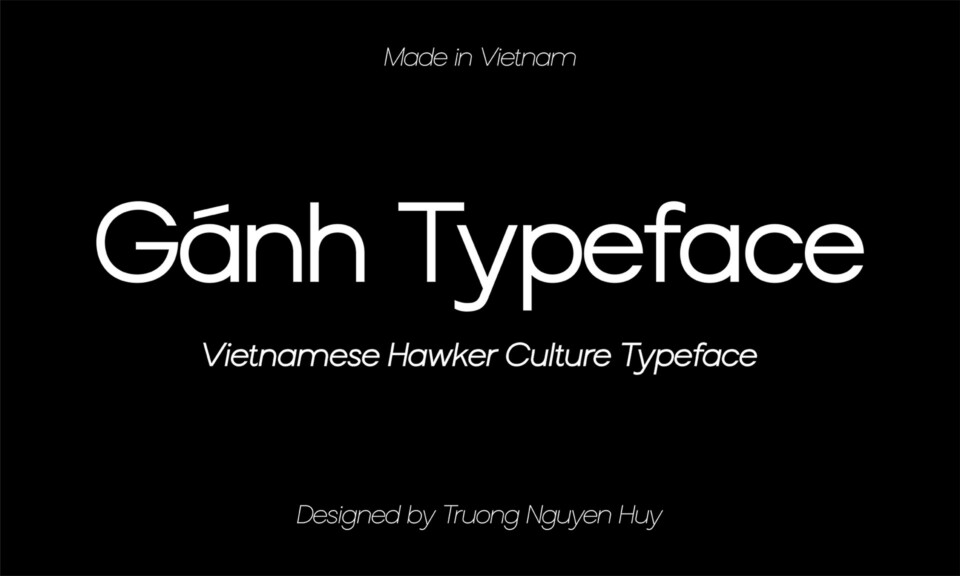
Font Gánh Typeface (4 otf files)
Giới thiệu về Font Gánh Typeface (4 otf files) và ý nghĩa thiết kế
Trong thế giới đồ họa hiện đại, việc tìm kiếm một bộ Font Miễn Phí mang đậm bản sắc văn hóa Việt Nam là điều vô cùng quý giá. Font Gánh Typeface (4 otf files) là một tác phẩm nghệ thuật chữ viết độc đáo, lấy cảm hứng từ hình ảnh đôi quang gánh tần tảo của người phụ nữ Việt. Bộ font này không chỉ đơn thuần là những ký tự số hóa mà còn chứa đựng cả một câu chuyện về sự nhẫn nại và nét đẹp lao động truyền thống. Với cấu trúc linh hoạt và đường nét tinh tế, bộ font này giúp các thiết kế trở nên gần gũi và có chiều sâu cảm xúc hơn bao giờ hết.
Các đặc điểm nổi bật của Font Gánh Typeface (4 otf files)
Định dạng chuyên nghiệp và tính ứng dụng cao
Bộ Font Gánh Typeface (4 otf files) bao gồm 4 định dạng OpenType chất lượng cao, cho phép người dùng tùy chỉnh linh hoạt trong các phần mềm thiết kế như Photoshop hay Illustrator. Mỗi tệp tin trong bộ 4 otf files đều được chăm chút kỹ lưỡng về khoảng cách và độ dày nét, đảm bảo tính thẩm mỹ đồng nhất trên cả bản in lẫn hiển thị kỹ thuật số. Đây là lựa chọn lý tưởng cho các dự án thiết kế bìa sách, poster sự kiện văn hóa hoặc bộ nhận diện thương hiệu mang phong cách hoài cổ nhưng vẫn giữ được sự tinh tế cần thiết.
Font Việt hóa đầy đủ cho giáo dục và sáng tạo
Điểm cộng lớn nhất là khả năng hỗ trợ tiếng Việt hoàn hảo, giúp các bạn học sinh và giáo viên dễ dàng ứng dụng vào bài giảng hoặc dự án học thuật. Sự kết hợp giữa nét chữ truyền thống và kỹ thuật typography hiện đại tạo nên một tổng thể hài hòa, giúp người xem dễ dàng tiếp nhận thông điệp một cách tự nhiên nhất.
Kết luận về bộ Font Gánh Typeface (4 otf files)